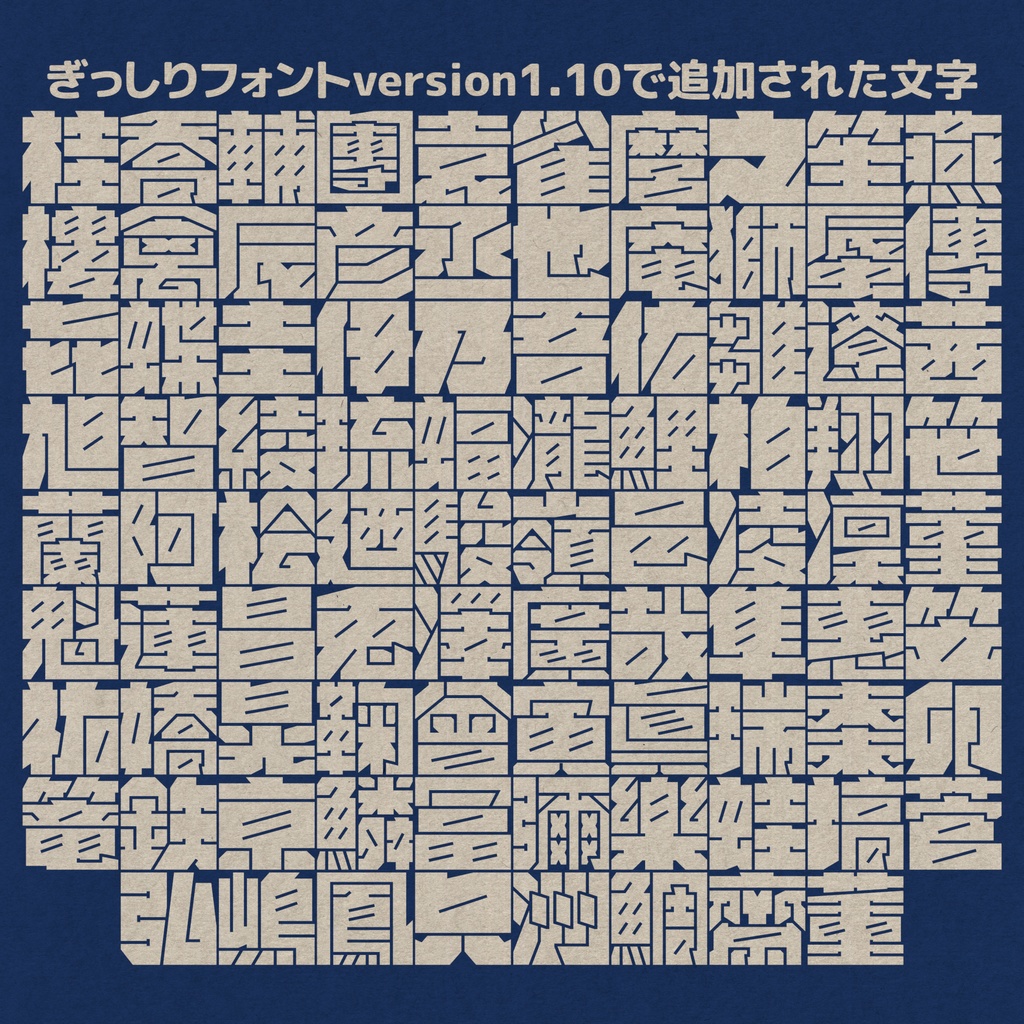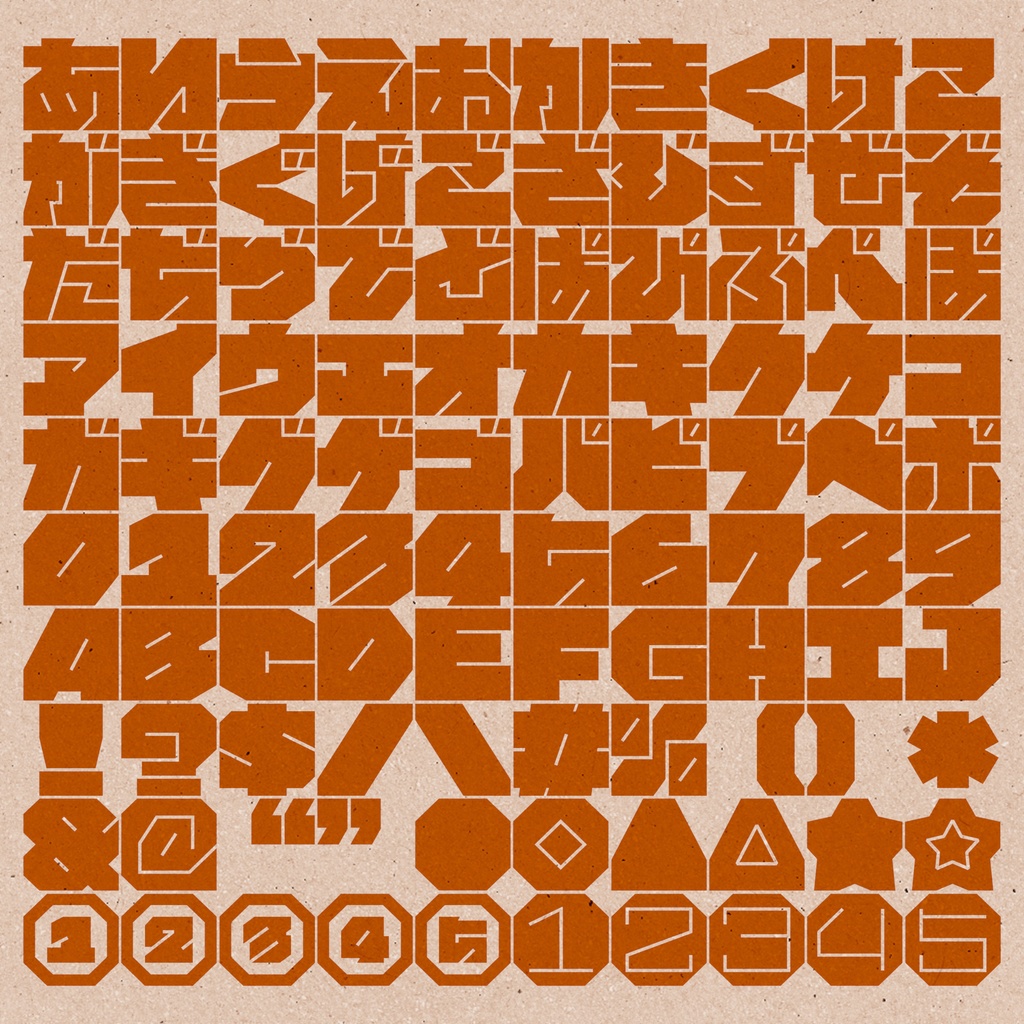
ちば けいすけぎっしりフォント(有料版)Digital4,950 JPYAdd to CartBuy a GiftAbout Gift商用・個人利用を問わずロゴやポスターに使えるTrueType形式のフォントです。 直線のみで構成され、ぎっしり詰まっているのが特徴です。かなりクセのある文字ですので、本文に使用すると非常に読みづらくなると思います。 英数字・ひらがな・カタカナ・一部の記号・常用漢字+αの漢字が収録されています。 2025年10月1日現在のプロの落語家・講談師・浪曲師・浪曲曲師・寄席色物・お囃子の名前が全部書けます(変体仮名以外)。 最近の更新◆2026.1.27 version 1.31 完成 「静」の字形が「清」になっていたのを修正しました。 ちば けいすけFontsひつじさるちば けいすけ2,750 JPYFontsぎっしりフォント(無料版)ちば けいすけ0 JPYFontsだてまきフォントちば けいすけ0 JPY